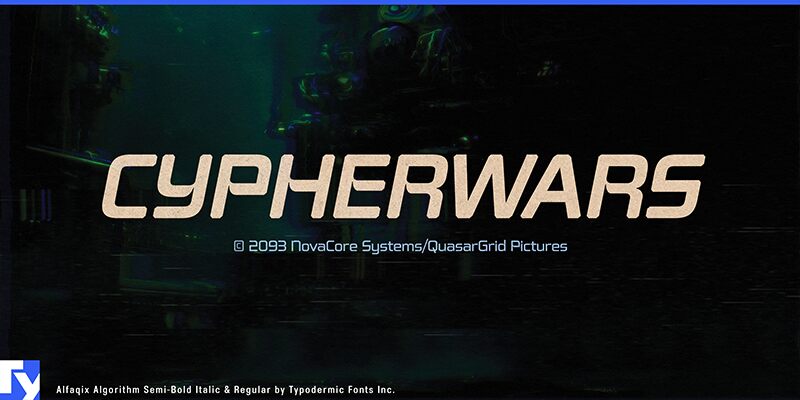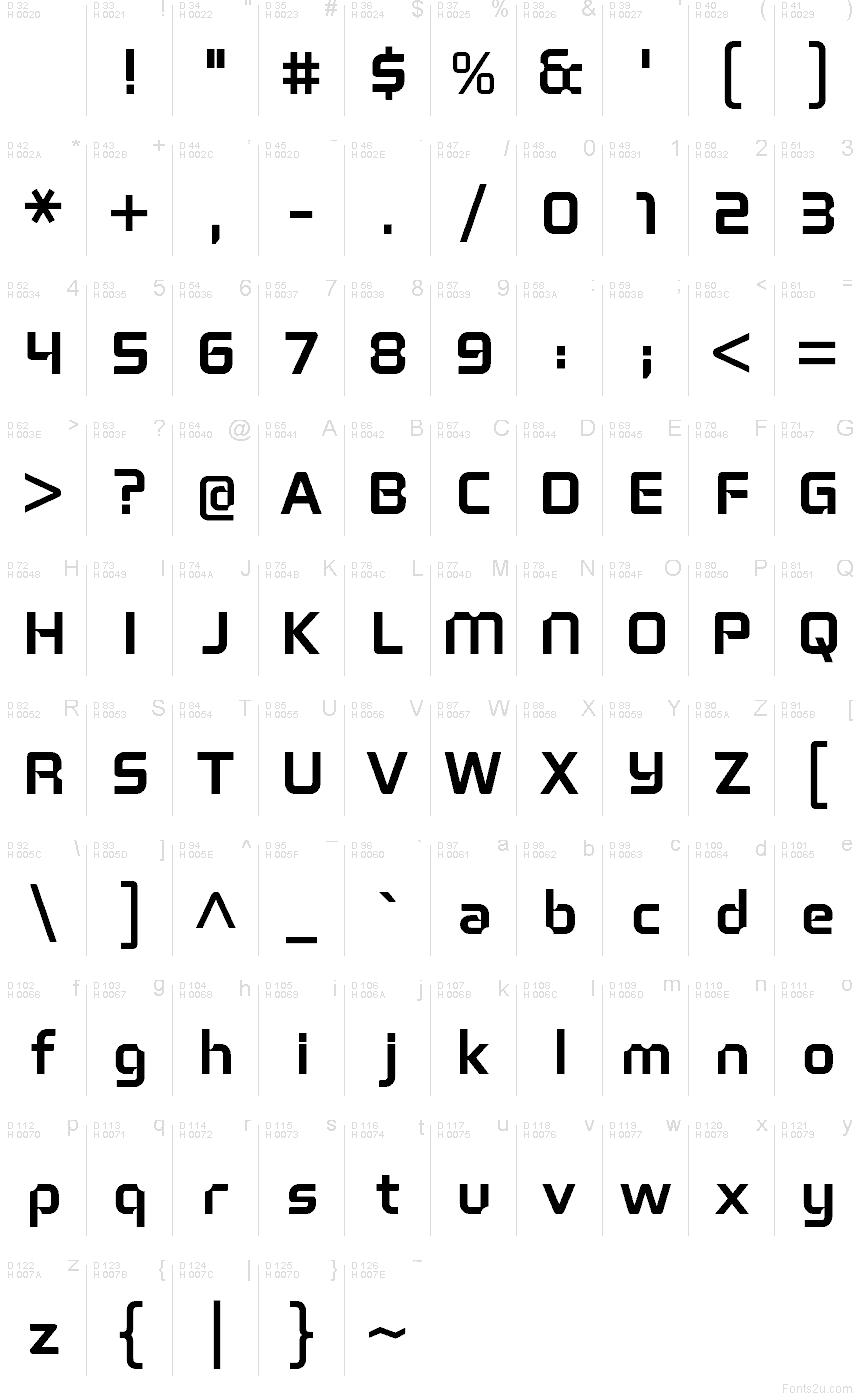
Alfaqix to kolekcja modularnych, inspirowanych techno krojów pisma, badających różne oblicza futurystycznej geometrii. Kwadratowe formy, ostre ścięcia, zaokrąglone końcówki i charakterystyczne mechaniczne wycięcia tworzą rodzinę projektów, które sprawiają wrażenie zaprojektowanych, cyfrowych i niepodważalnie nowoczesnych. Czerpiąc inspirację z wyświetlaczy danych, segmentów LCD, serwomechanizmów i futuryzmu ery Y2K, kroje Alfaqix doskonale nadają się do interfejsów, pulpitów nawigacyjnych, brandingu technologicznego, motion designu i układów redakcyjnych, które wymagają czystego, high-tech brzmienia. Dzięki szerokiemu wsparciu dla języków europejskich opartych na alfabecie łacińskim, Alfaqix zapewnia precyzyjną, przyszłościową typografię dla współczesnego designu.
Prezentacja i próbka wizualna czcionki Alfaqix Servo Semi Bold